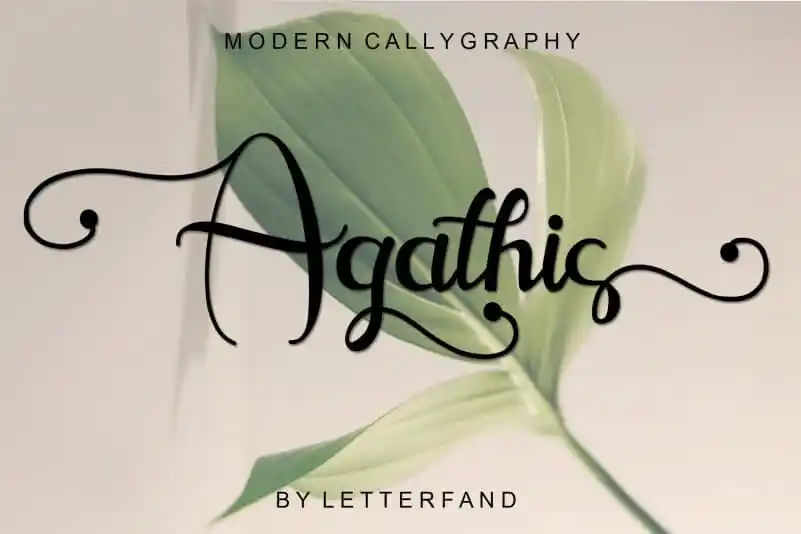
Agathis Calligraphy Font – Fonte Grátis
Agathis Calligraphy Font
A Agathis Calligraphy Font é uma escolha perfeita para quem busca uma tipografia delicada e elegante que transmite beleza e equilíbrio. Criada pelo talentoso designer Ahmad Afandi, essa fonte tem um design fluído e manuscrito, oferecendo um caráter grato e bem balanceado. Suas linhas fluidas proporcionam uma experiência visual agradável e confortável para qualquer projeto, seja ele em designers de ícones, marcas ou logotipos. Este é um recurso que combina perfeitamente com um amplo espectro de designs, tornando-o uma opção ideal para quem busca uma fonte única e de alta qualidade que oferece um toque diferenciado a qualquer projeto gráfico.